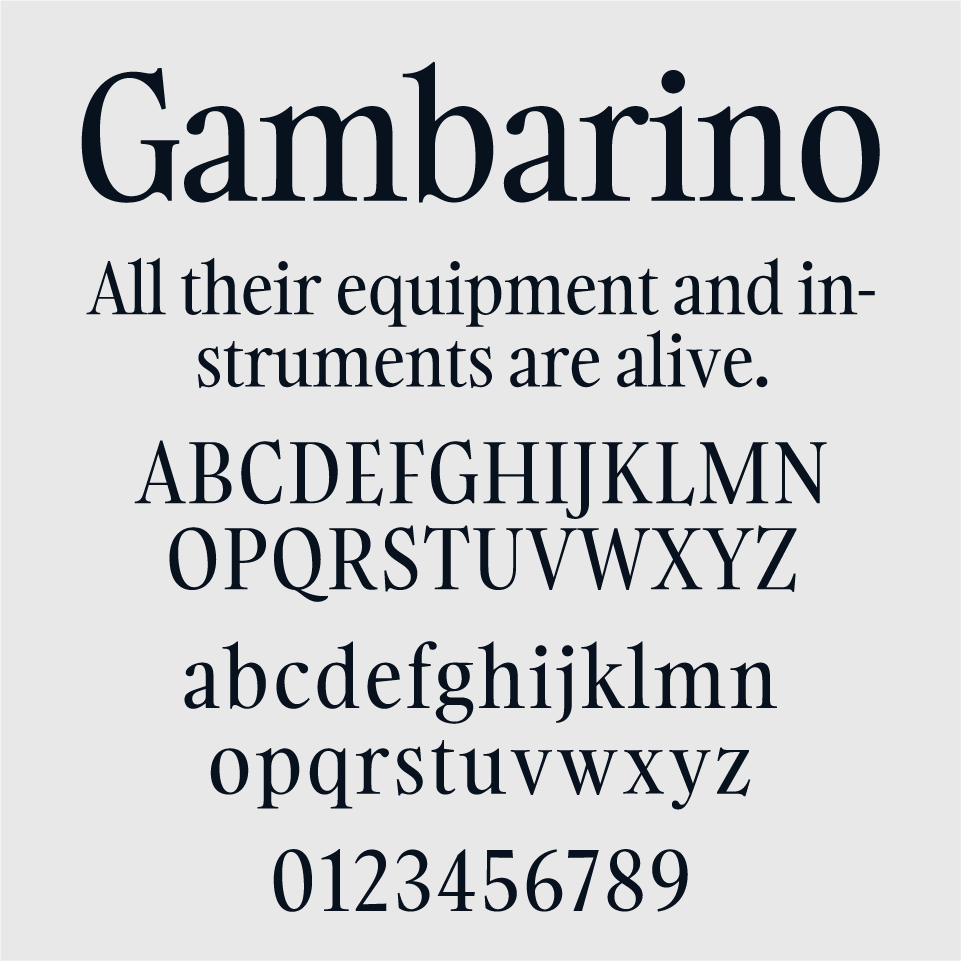
Gambarino フォントは、クラシカルな書体の品格を保ちつつ、現代的な丸みとゆらぎを取り入れた、優雅でやわらかな印象のセリフ体です。
伝統的なフォルムでありながら、都会的な印象もあり、決して堅苦しさを感じさせない絶妙なバランスが魅力です。
本文用としても安定感があり、文学作品やブランドロゴなど、格式と親しみの両立が求められる場面で力を発揮します。特に小文字の造形に遊び心があり、タイポグラフィにちょっとした余白を与えてくれるような印象。上品でありながら、肩の力が抜けた優しさのあるフォントです。